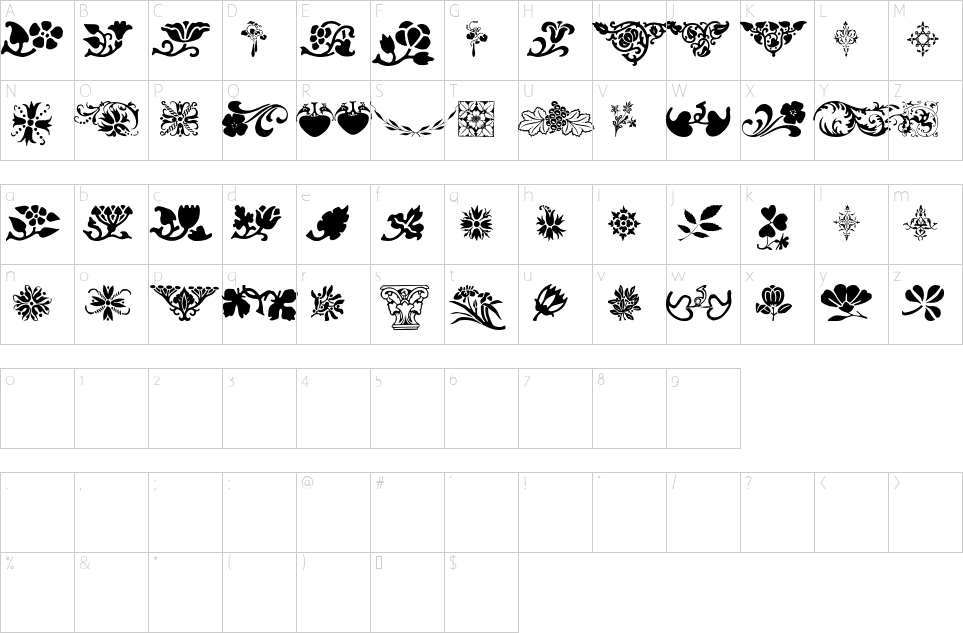
A fonte Printers Ornaments One é uma opção única e divertida para designers gráficos, especialmente aqueles que buscam adicionar um toque único às suas criações. Ela foi criada pelo designer desconhecido Dieter Steffmann e oferece uma variedade de ornamentos e padrões que podem ser usados para criar efeitos interessantes em títulos e textos. Esta fonte de 1001 Free Fonts oferece um grande número de opções que podem ser usadas de maneiras diferentes, permitindo que você personalize o seu design de acordo com suas necessidades. Com uma variedade de padrões em um estilo moderno e elegante, Printers Ornaments One é uma excelente opção para aqueles que procuram uma fonte diversificada e inovadora para seu próximo projeto. Com apenas alguns cliques, você pode transformar seu design digital de uma maneira que chama atenção, usando estas incríveis ornamentações de impressão. Download Printers Ornaments One agora e comece a explorar as inúmeras possibilidades desta fonte grátis e versátil.